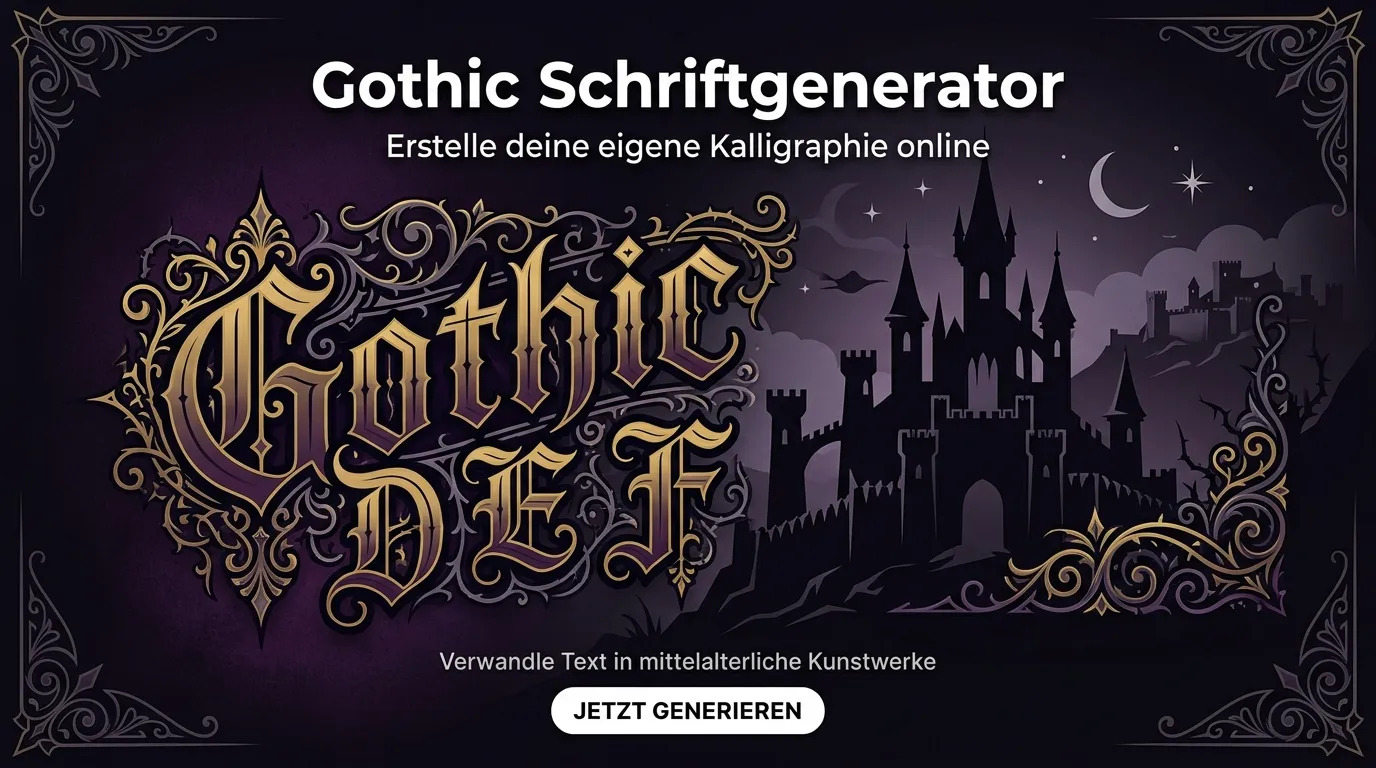
Erstelle beeindruckenden Text in gotischer Schrift: von Fraktur über Blackletter bis Old English. Perfekt für Tattoos, Gaming-Tags, Band-Logos und Instagram. Kostenlos, ohne Anmeldung, direkt im Browser.
Deutsche Umlaute und ß haben keine Gothic-Entsprechung im Unicode-Standard und erscheinen daher in normaler Schrift neben den umgewandelten Buchstaben. Das ist eine unvermeidliche technische Einschränkung aller Gothic-Generatoren, nicht ein Fehler unseres Tools.
Gothic-Schrift für Gaming, Tattoos und Social Media
Gothic-/Blackletter-Schrift ist eine der vielseitigsten dekorativen Schriftfamilien: In der Gaming-Community signalisiert sie Stärke und Mystik: perfekt für Discord-Servernamen, Fortnite-/Valorant-Spielertags und Twitch-Handles. In der Tattoo-Szene ist Blackletter einer der beliebtesten Stile für Namen, Daten und kurze Sprüche.
Auf Social Media (Instagram, TikTok, WhatsApp) hebt sich Gothic-Text sofort von der Standard-Schrift ab und erzeugt einen dunkel-eleganten, auffälligen Look: ideal für Bio-Texte, Band-Promotion oder thematisch passende Accounts.
Eng verwandt mit Gothic ist die altdeutsche Frakturschrift-Varianten , die speziell auf historisch-deutsche Stile fokussiert.
Die Geschichte der gotischen Schrift: Von Gutenberg bis Streetwear
Gotische Buchschrift (Textualis) entstand im 12. Jahrhundert in den Klöstern Westeuropas. Die markanten, gebrochenen Buchstabenformen waren eine Reaktion auf den hohen Pergamentpreis: durch engere, eckigere Buchstaben passte mehr Text auf eine Seite. Johannes Gutenberg wählte für seine berühmte Bibel (1455) eine gotische Schrift als Vorlage.
Die Fraktur-Variante (ab ~1500) wurde zur vorherrschenden Druckschrift im deutschsprachigen Raum. Heute erlebt der Stil eine Renaissance in der Popkultur: Streetwear-Marken, Metal-Bands, Tattoo-Studios und digitale Designer nutzen Gothic/Blackletter als Stilmittel: befreit von historischem Ballast, als rein ästhetisches Statement.
Was ist der Unterschied zwischen Gothic, Fraktur und Blackletter?
Diese drei Begriffe werden oft synonym verwendet, bezeichnen aber unterschiedliche Dinge: „Blackletter" ist der Oberbegriff für alle gebrochenen Schriften. „Gothic" (gotisch) bezeichnet den ältesten Blackletter-Stil (Textualis, ab ~12. Jahrhundert). „Fraktur" ist ein spezifischer, jüngerer Blackletter-Stil (ab ~16. Jahrhundert), der in Deutschland bis 1941 als Standard-Druckschrift galt. Im Alltag meinen die meisten Nutzer mit „Gothic Schrift" einfach den dekorativen Blackletter-Stil.
Kann ich Gothic-Schrift für ein Tattoo verwenden?
Ja: Gothic-/Blackletter-Schrift ist einer der beliebtesten Tattoo-Stile weltweit. Verwende den Generator als Vorschau und Inspiration. Für die endgültige Tattoo-Vorlage empfehlen wir, mit einem erfahrenen Tattoo-Künstler zusammenzuarbeiten, der die Buchstaben an deine Körperstelle und gewünschte Größe anpassen kann.
Warum ist Gothic/Fraktur-Schrift in Deutschland historisch sensibel?
Frakturschrift war bis 1941 die Standard-Druckschrift in Deutschland. Aufgrund ihrer Verwendung während der NS-Zeit und dem anschließenden Verbot (Normalschrifterlass 1941) tragen Fraktur und verwandte Schriften in Deutschland eine historische Ambivalenz. Heute wird Gothic-/Blackletter-Schrift international und in der Popkultur (Metal, Streetwear, Tattoos) selbstverständlich und wertfrei verwendet: die historische Dimension ist aber wichtig zu kennen.